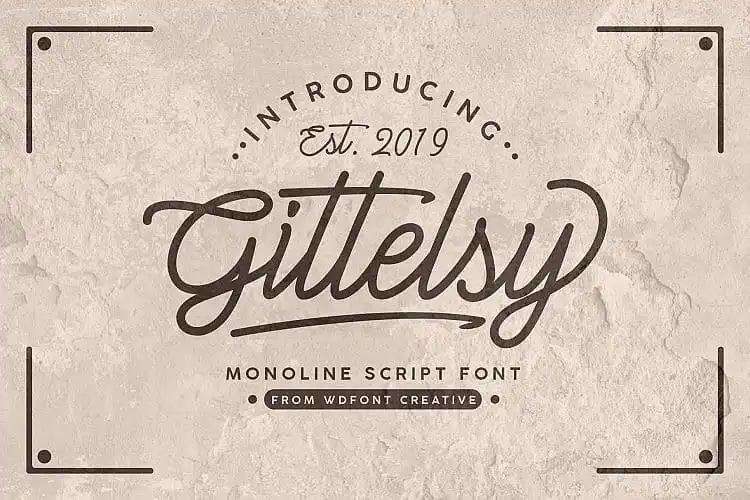
Gittelsy Monoline Script Font – Download Grátis
Aqui está uma versão descritiva para a página de download da font ‘Gittelsy Monoline Script Font’: Introduzimos Gittelsy Font para você, um novo e fascinante script moderno. Criado pela equipe do wdfont, esse design inovador incorpora o estilo adorado da calligrafia artesanal. A fonte “Gittelsy Monoline Script” é perfeitamente adaptada para uso diário, oferecendo um estilo de linhas monolíneas moderno. Suas possibilidades de utilização são vastas e variadas – desde a criação de logotipos e selos até o design de camisetas e postagens nas redes sociais. O designer também pensou em você com alternativas de caracteres que foram divididas nos recursos Open Type, como Swash, Set Estilístico, Alternativa Estilística e Alternativa Contextual. Essas opções adicionais fornecem um toque único e personalizado às suas criações, tornando a fonte ainda mais versátil e adaptável para diferentes tipos de trabalho. Descubra agora o poder desta nova fonte, disponível para uso em sua próxima peça de design ou marca, transformando seu trabalho diário no seu próprio show!